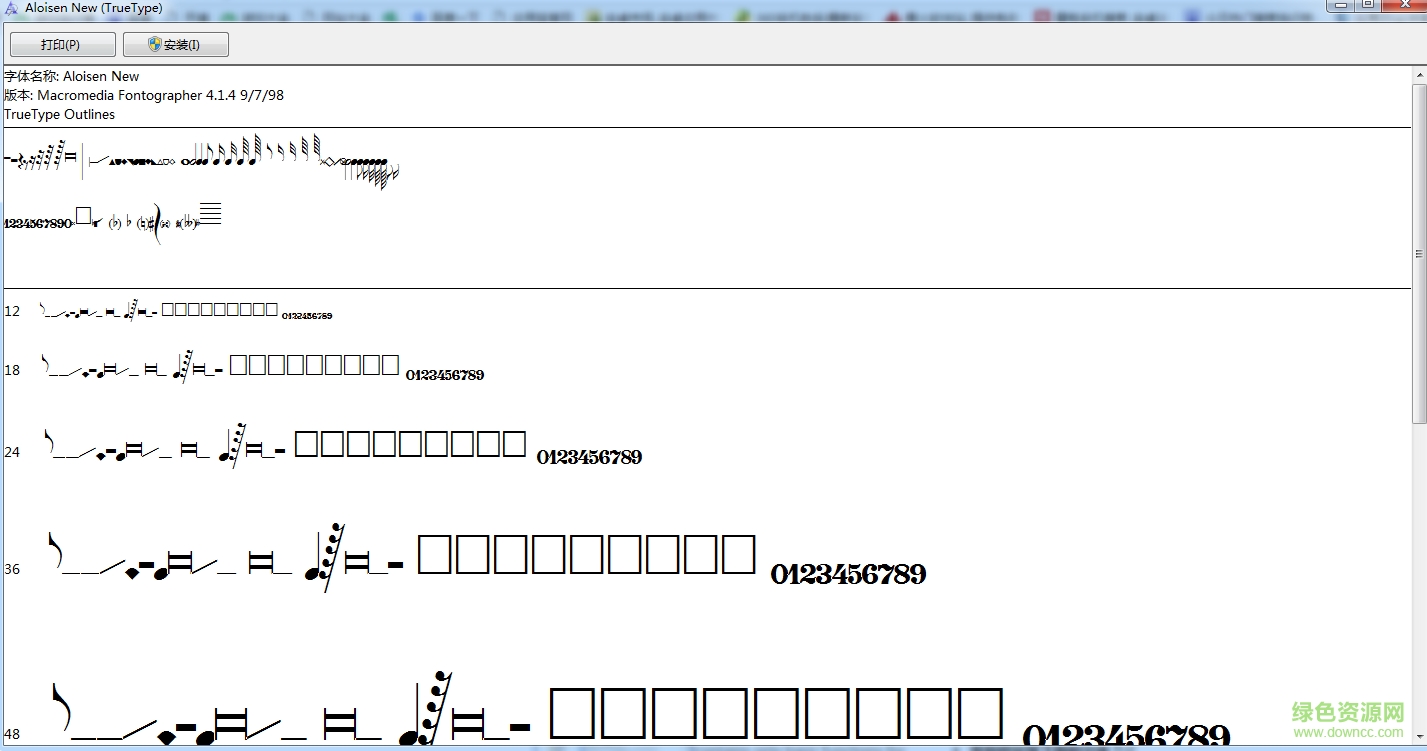
aloisen new字體是一款特殊的五線譜字體,包含了詳細(xì)的音譜符號(hào)和數(shù)字符號(hào),綠色資源網(wǎng)為大家免費(fèi)搜集了這款字體,歡迎大家前來(lái)下載!
AloisenNew字體是一個(gè)五線譜字體,一般情況下會(huì)在某些五線譜軟件中用到,比如:overture,如果你的系統(tǒng)缺少它,就要安裝才可以正常顯示簡(jiǎn)譜!